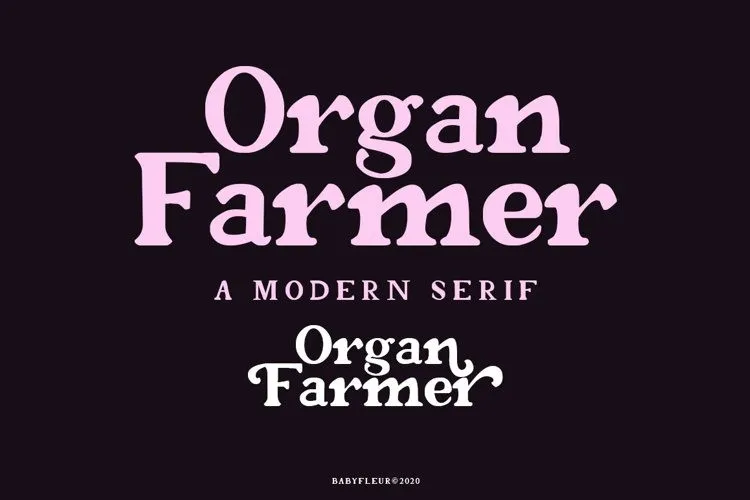
A Organ Farmer é uma elegante e vintage serif font desenvolvida pela Babyfleur para uso na categoria Serif Fonts. Ela é perfeitamente adequada tanto para aplicações empresariais quanto para eventos formais, como cartões de convite ou outros formatos simbólicos. Esta fonte tem um toque aveludado e elegante que se destaca, o que a torna perfeita para criação de logotipos e design gráfico formal. Ideal tanto para uso em branding quanto em projetos criativos exigentes como cartões de convite ou outros formatos formais, essa fonte apresenta um nível de flexibilidade impressionante. Suas linhas arredondadas e detalhes finamente trabalhados proporcionam uma aparência sofisticada e estilizada que se adaptará perfeitamente a qualquer tipo de projeto gráfico. Esta font é a escolha ideal para designers profissionais, criando um impacto imediato e marcante em qualquer layout. Suas características elegantes e vintage garantem que sua marca ou evento saia na frente do resto da concorrência, com uma aparência que reflete tanto o seu estilo quanto a qualidade de seu produto ou serviço.